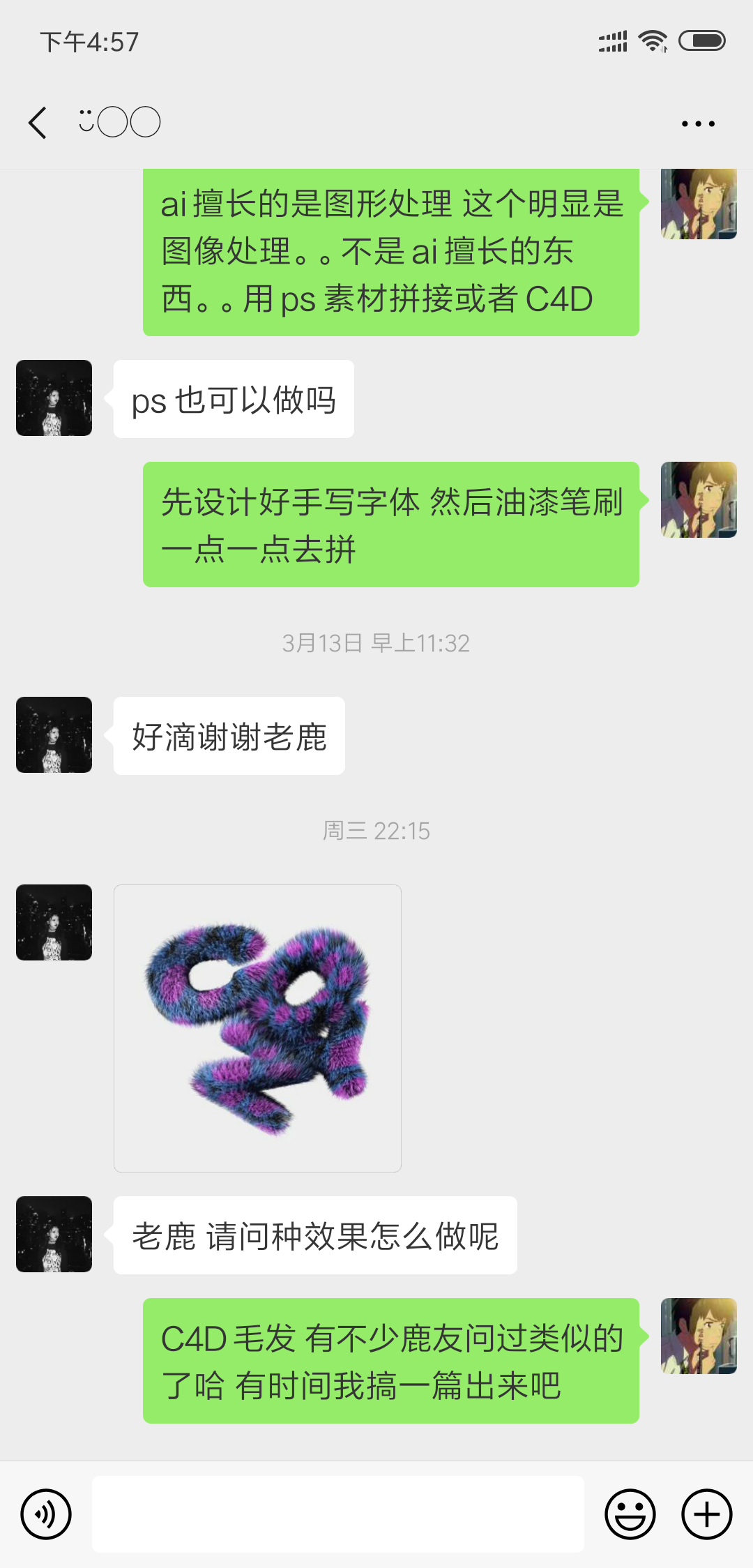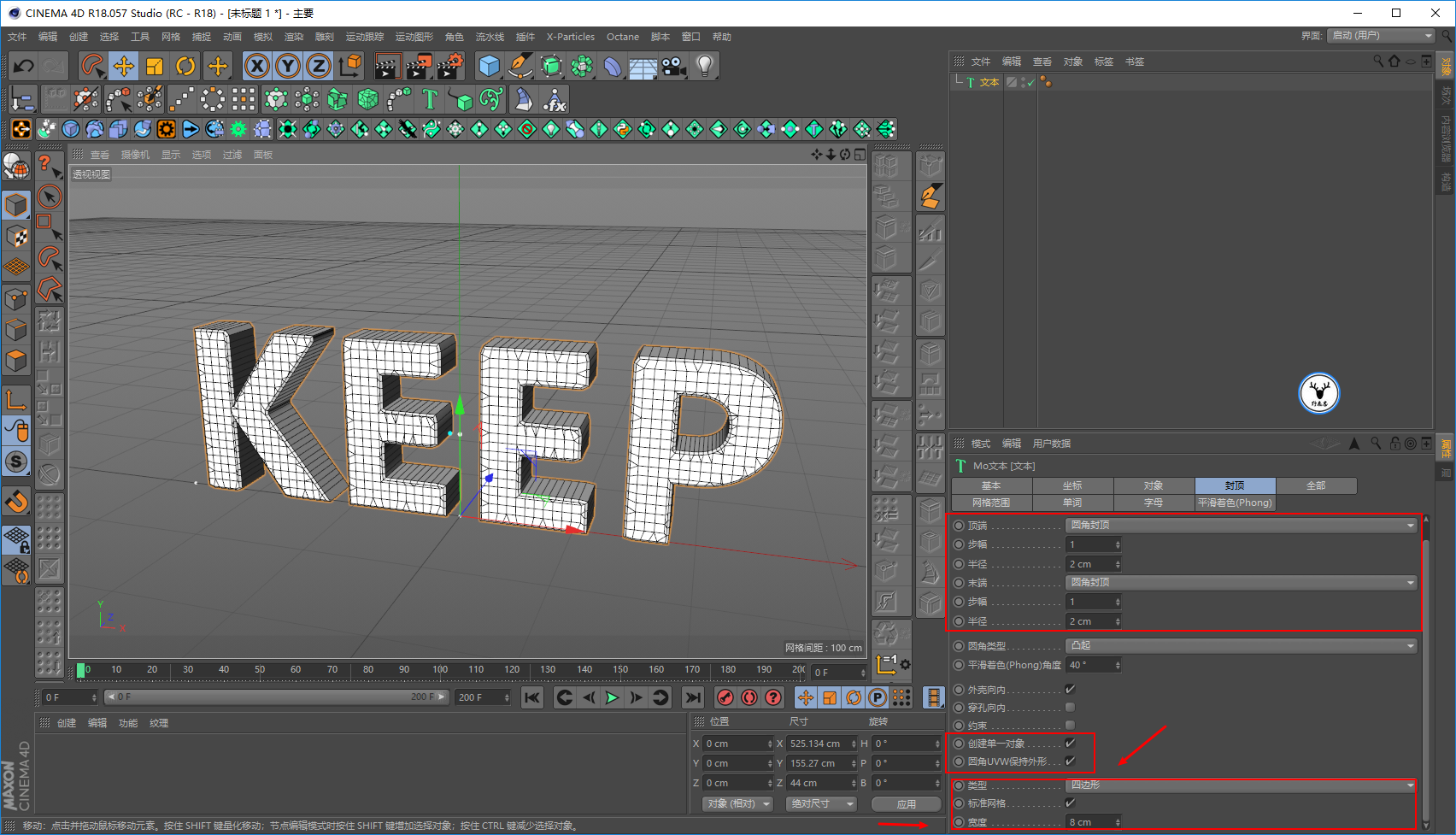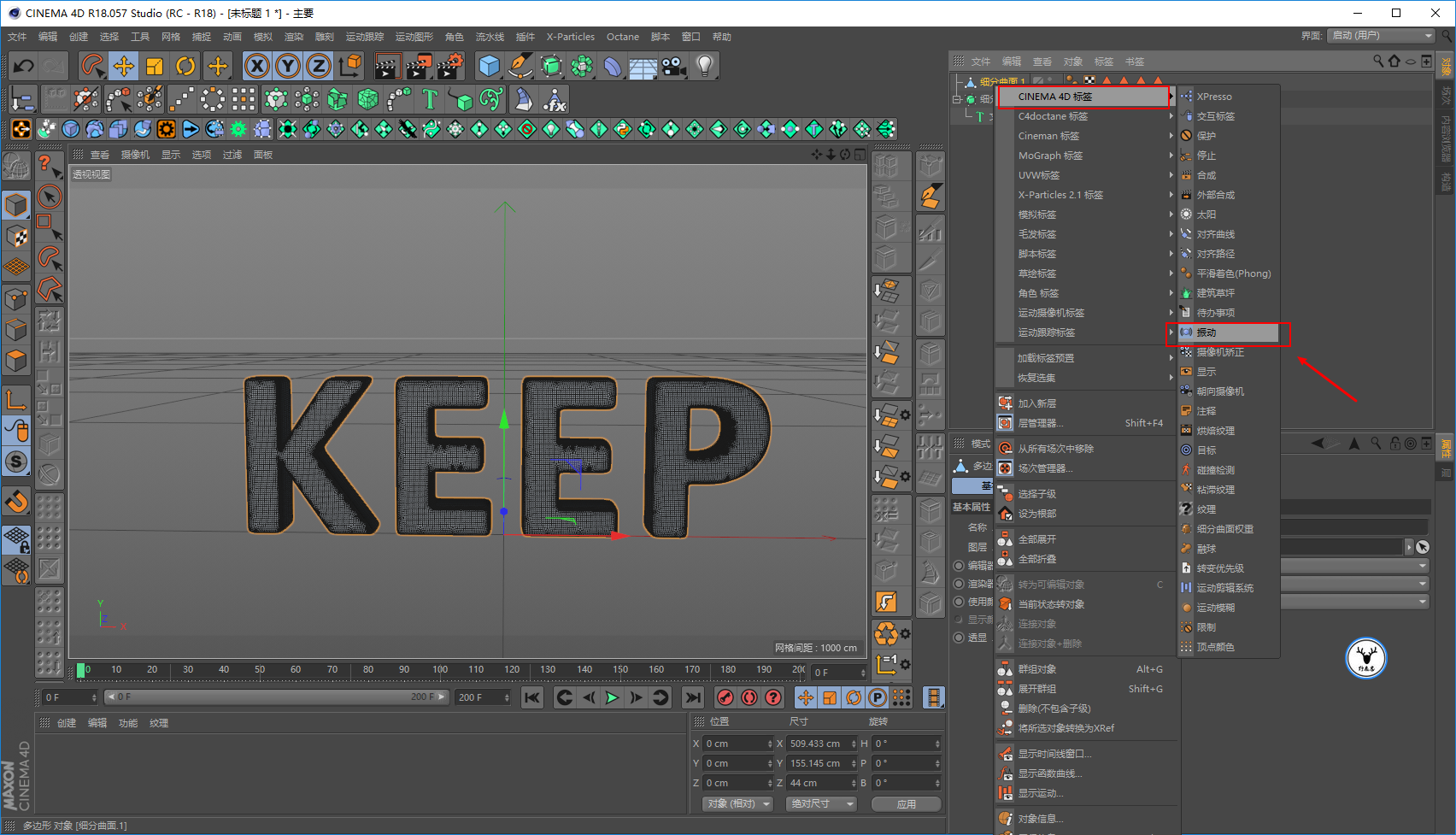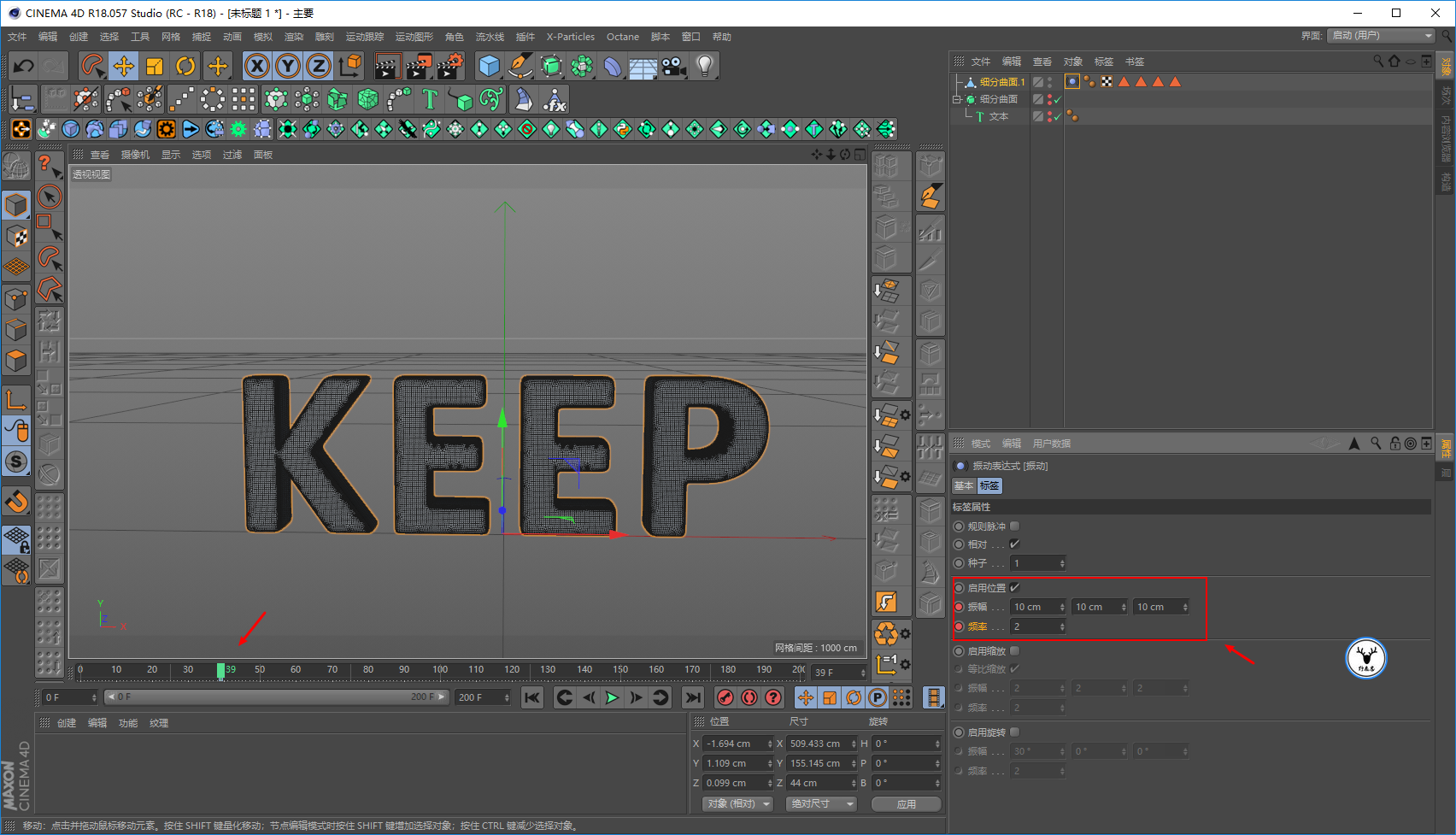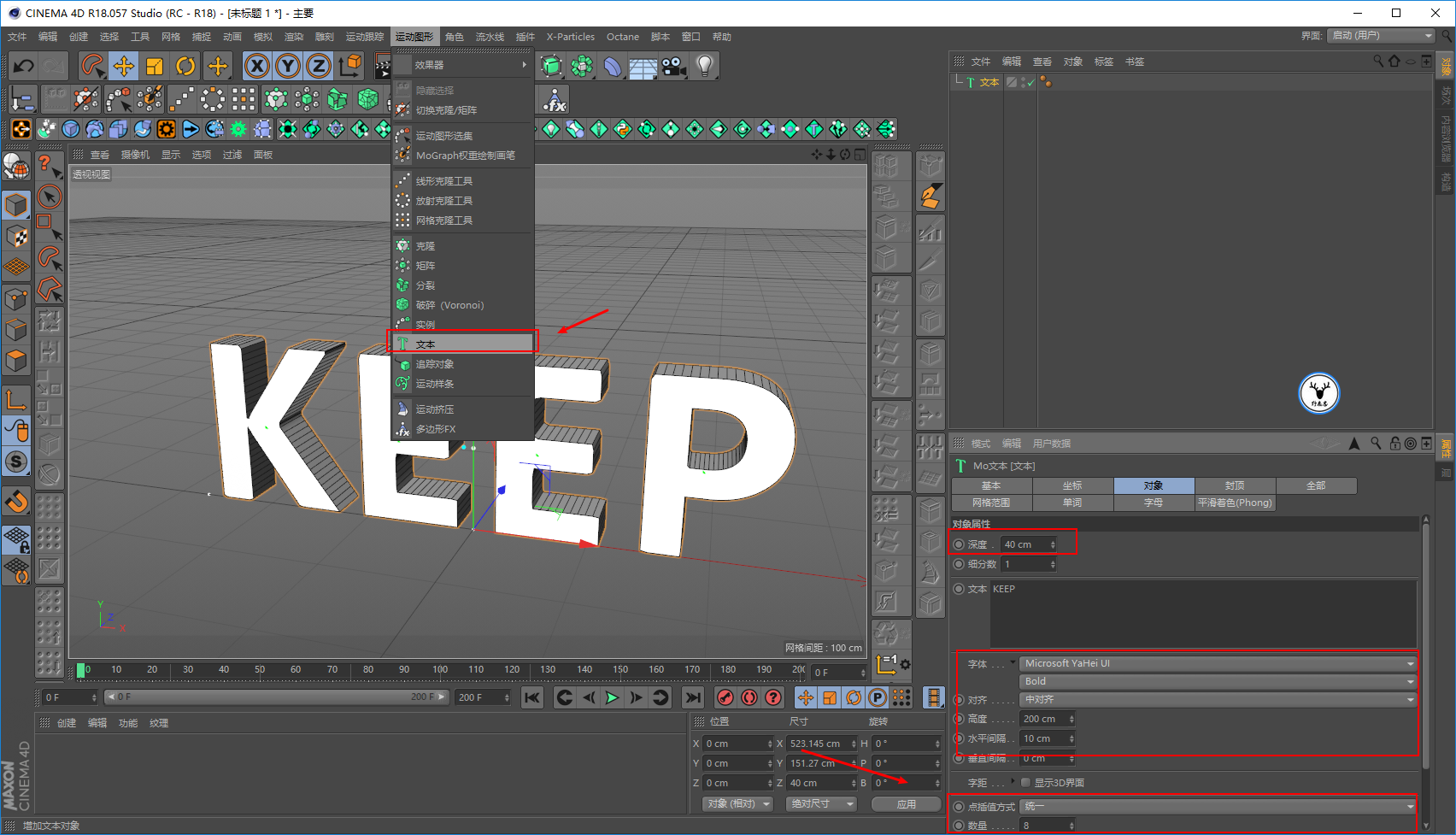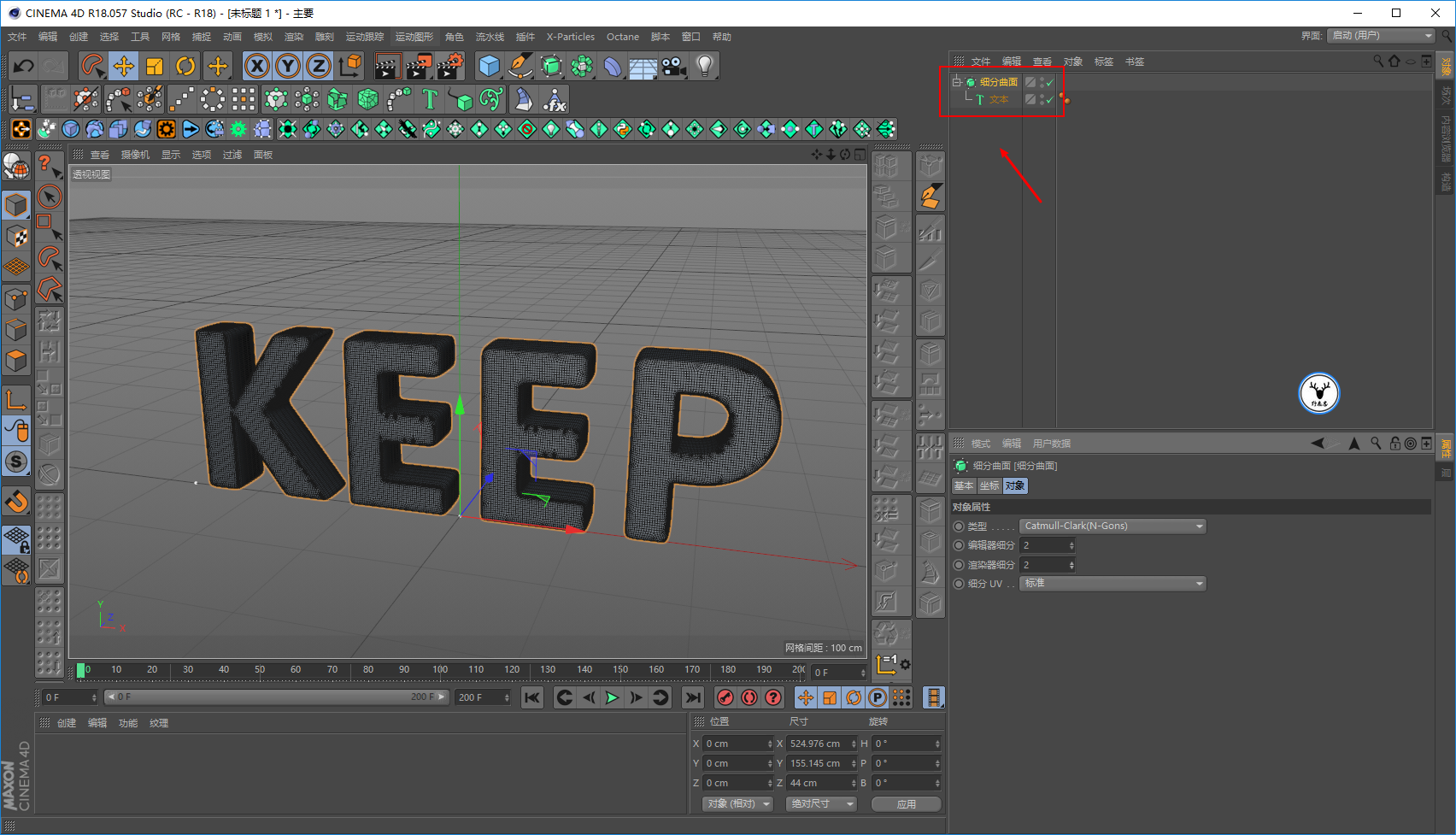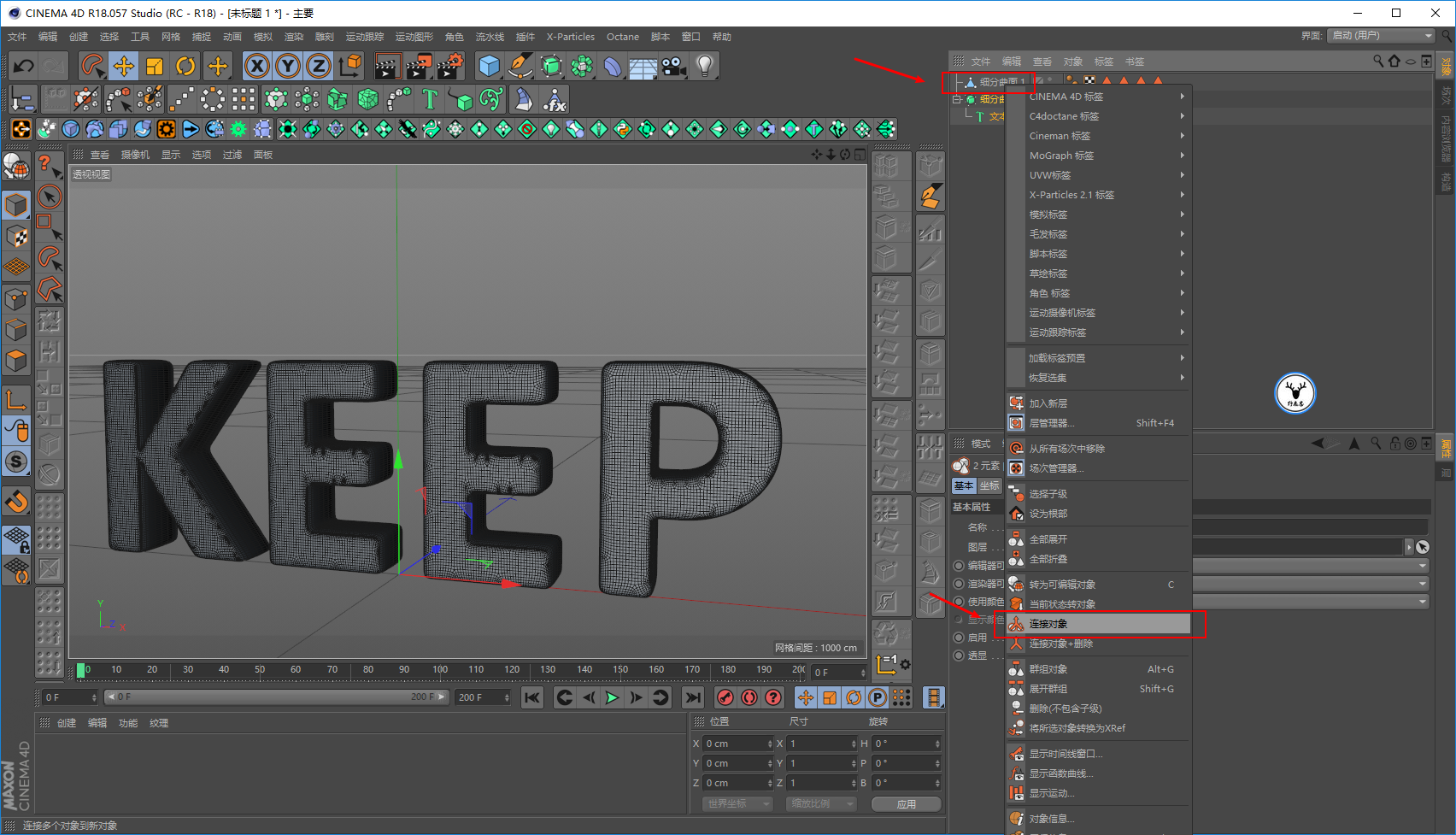
一起来制作一个炸毛了的文字动画吧
微博上收到一个动画效果的问题,我们导出动图来看看吧:
动图压缩的比较厉害,大家知道那个意思就好。大概就是文字先随机的晃动,晃动着晃动着就炸毛了。
这个效果其实是典型的C4D毛发的运用,包括还有其他一些鹿友的问题:
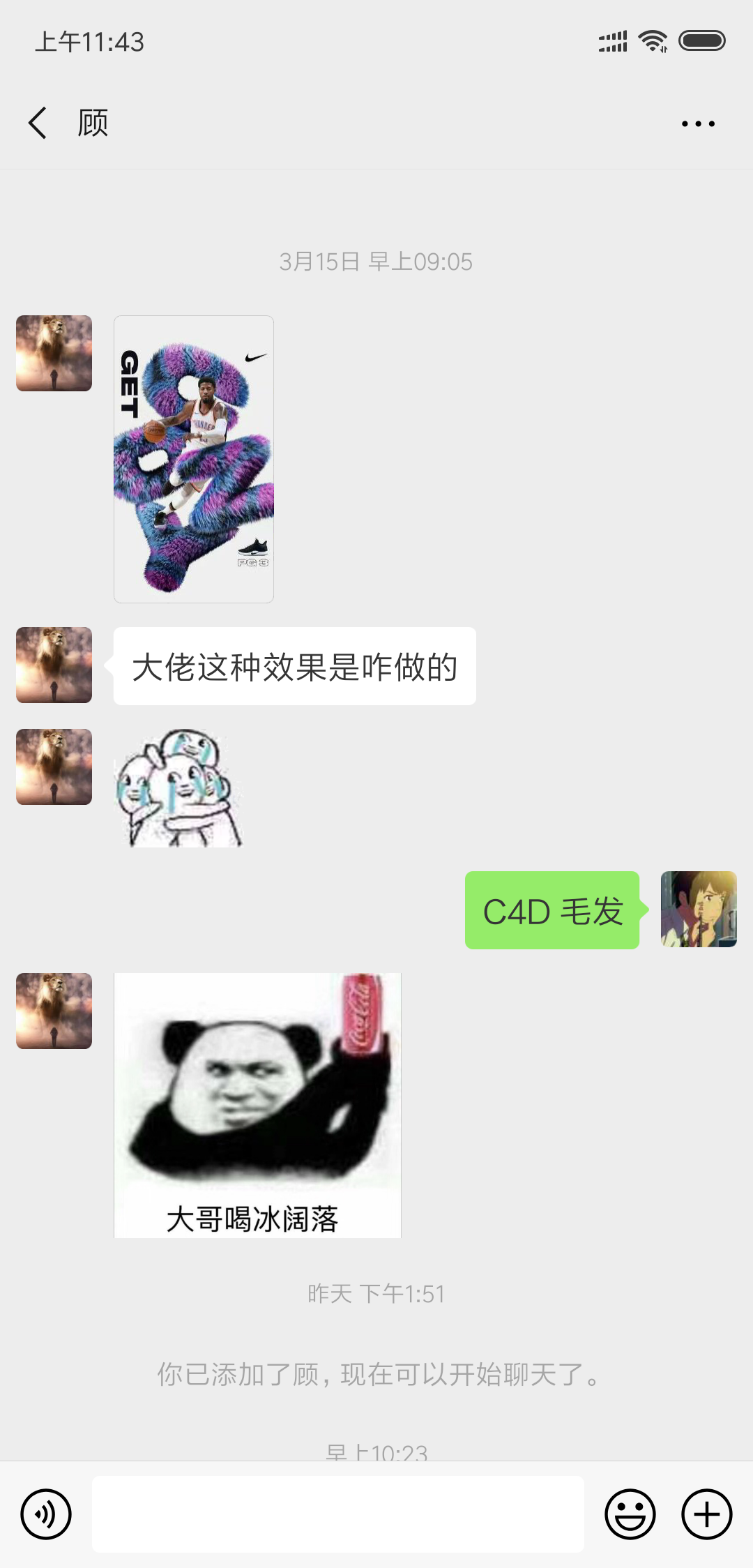
C4D的毛发功能其实很强大,并且也非常容易出效果,以上几位鹿友问的效果图其实只是用到了毛发里比较常见的一些功能。
来吧,今天我们就来看看如何制作一个炸毛了的文字动画吧!
打开C4D,把帧速率设置为25帧,总共就做200帧也就是8秒的动画吧:
新建一个文本对象,输入文字,选择一个比较粗一点的字体吧。
至于深度以及水平间隔这个大家看着办就好,记得把差值方式选为统一:
封顶的参数大家看着办就好,勾选创建单一对象以及圆角UVW保持外形。
类型选择为四边形,勾选标准网格,宽度适当调整一下就好,这样文字的布线会相当均匀一点:
再给文字添加细分曲面,细分数2就好了:
然后将细分曲面的两个对象连接成为一个对象并且切换到点级别优化一下:
先做晃来晃去的动画吧,给对象添加一个振动标签:
勾选启用位置,关键帧的位置大家凭感觉来吧,我这里是在39帧以前,让振动的位移为10,频率2:
到100帧的时候,让位移变成20,频率3:
到200帧的时候,位移变成0,频率为2,这样字母就有一开始晃动,中间剧烈晃动然后慢慢停下来的感觉了:
晃动的动画做好了以后,就可以添加毛发了,选中对象执行模拟-毛发对象-添加毛发:
这里引导线以及毛发的参数含义大家需要区分一下,简单理解,引导线是视图用于控制毛发的形态或者分布等,不代表毛发最终渲染的数量。
如果数量多了操作起来会很卡,所以可以让引导线的数量少一点。
而毛发参数中的数量就代表着最终渲染的毛发数量,例如我这里是30W根:
因为对于毛发材质来说,灯光也很重要,所以先打灯吧,然后再看着效果调整材质。
如图所示,我就很常规的打了三盏灯,至于灯光的强弱大家看着效果来吧:
上材质吧,新建材质球拖给文字,在颜色通道中加载一张贴图:
反射通道我就随意的改了一下默认高光的参数,然后给了一个菲涅尔遮罩,让正面看起来反射不那么强烈:
毛发材质里,颜色通道里发根加载同样的贴图:
高光通道里,降低一下强度等:
粗细也搞一下吧:
长度同样搞搞,这些都是看着效果来的哈,参数不是唯一:
比例也搞搞:
最后再搞点集束:
接下来可以做毛发的动画了,首先大家要记住一点,毛发对象的影响面板有一个重力数值默认是-9.81。
所以毛发材质自带了一个动力学会受到重力的影响:
毛发材质里,我们让文字一开始没有毛发,所以长度大概在20帧的样子为0打上关键帧:
由于我们刚才做振动动画的时候,100帧是最剧烈的那个点,所以100帧的时候让长度恢复到80%:
同时毛发对象里,第0帧的时候先把启用关闭打上关键帧:
然后第20帧的时候,勾选启用再打上关键帧,这样毛发就会从第20帧才开始起作用,并且长度有一个0到80的变化:
动力学面板里,我们让保持静止的数值在50帧以前都是0:
第100帧晃动得最厉害的时候,让保持静止的参数为80:
然后在最后一帧的时候,静止保持的参数为50打上关键帧。
这样通过引导线我们就可以看到毛发看起来就是一开始比较软,在晃动最厉害的时候炸毛了,然后慢慢又软下来的感觉:
到这里其实动画其实基本上就制作好了,但是还有一点需要注意一下,因为我们的毛发实际是从第20帧才开始出现的:
由于毛发、文字都会受到灯光的影响,再加上毛发的投影一系列原因会导致有了毛发以后的文字总体看起来明显比没有毛发之前暗。
如果做成动画的话,这样看起来就会比较突兀:
所以我这里采用的办法是在20帧之前,让对象正面的灯光强度降低一点:
让它在下一帧的时候,再立刻恢复强度,这样看起来亮度的过渡就没有那么突兀了:
摄像机固定视角,这一步不用说吧:
然后设置里设置渲染出图的尺寸以及帧速率,渲染全部帧:
保存格式为png,勾选A通道:
抗锯齿也可以给一下:
最后再导入到PS里加个背景、调色看看静图和动图的效果吧: